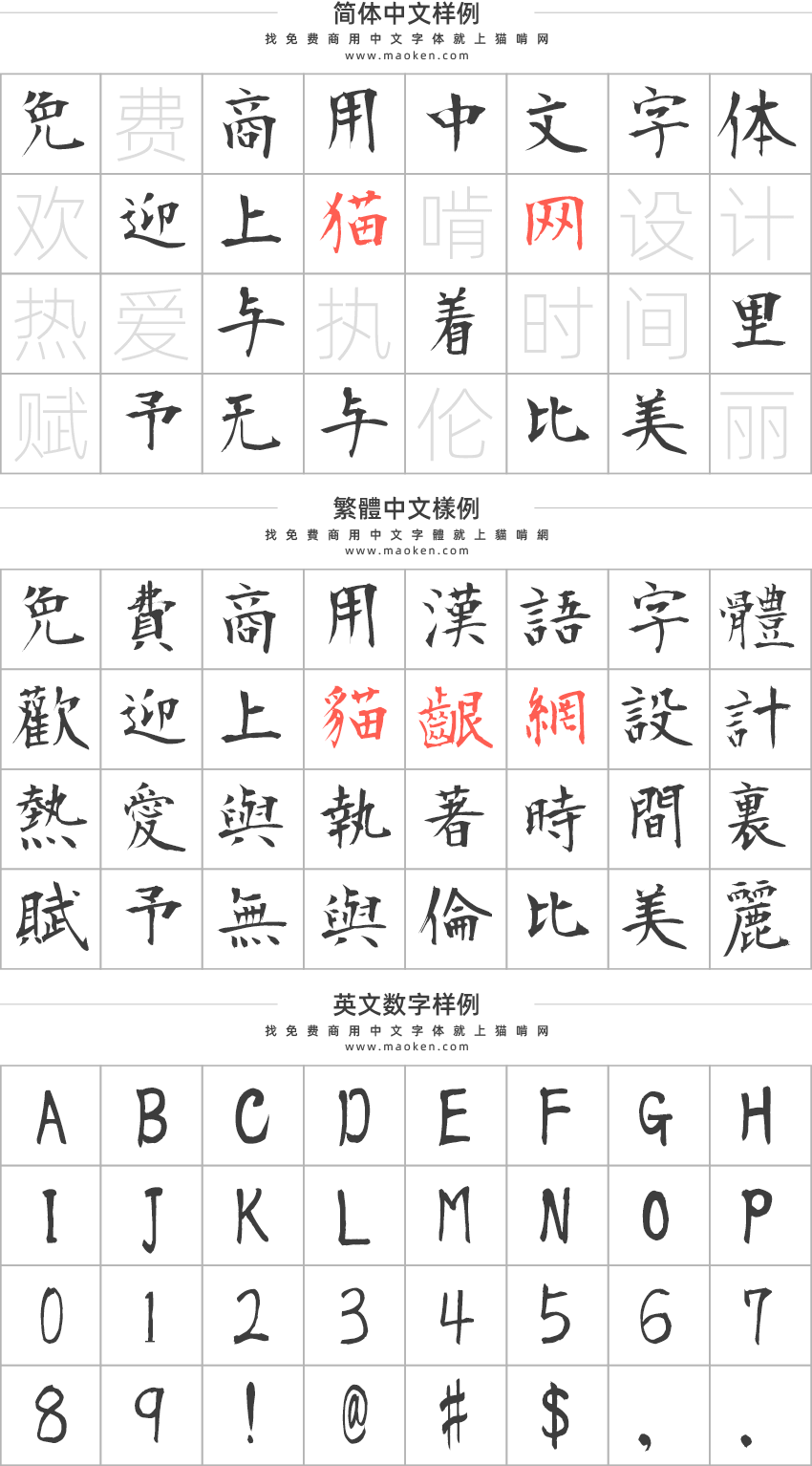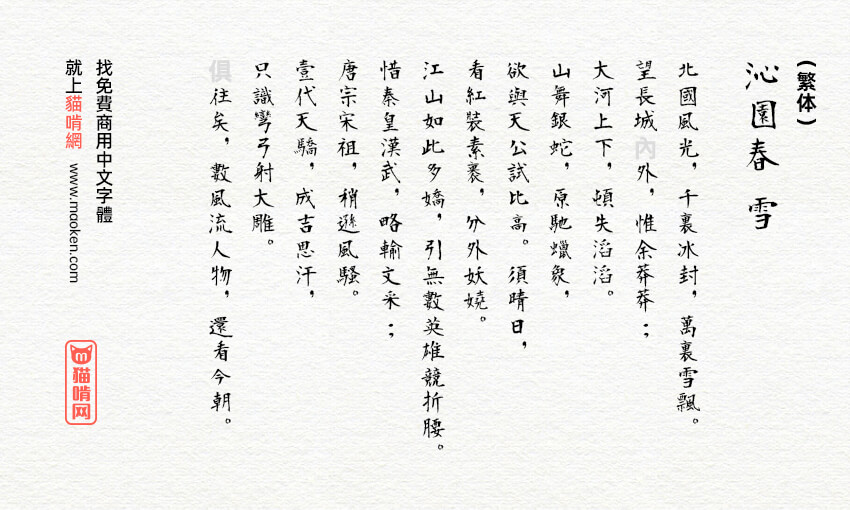
衡山毛笔体:日本青柳衡山又一款毛笔字体免费商用
字体作者:青柳衡山 (其他语种) 字体字重:1个
字体名称:衡山毛笔体(日文名:衡山毛筆フォント) PS中字体名称:衡山毛筆フォント Regular
衡山毛笔体是书法家青柳衡山老师挥毫书写的字体。 收录的字数约为13,000字。 由于字体采用的日本的JIS标准,所以支持的简体字数不算多,但是繁体却是比较齐全的。 如果喜欢衡山毛笔体这款字体,就赶紧下载使用吧。